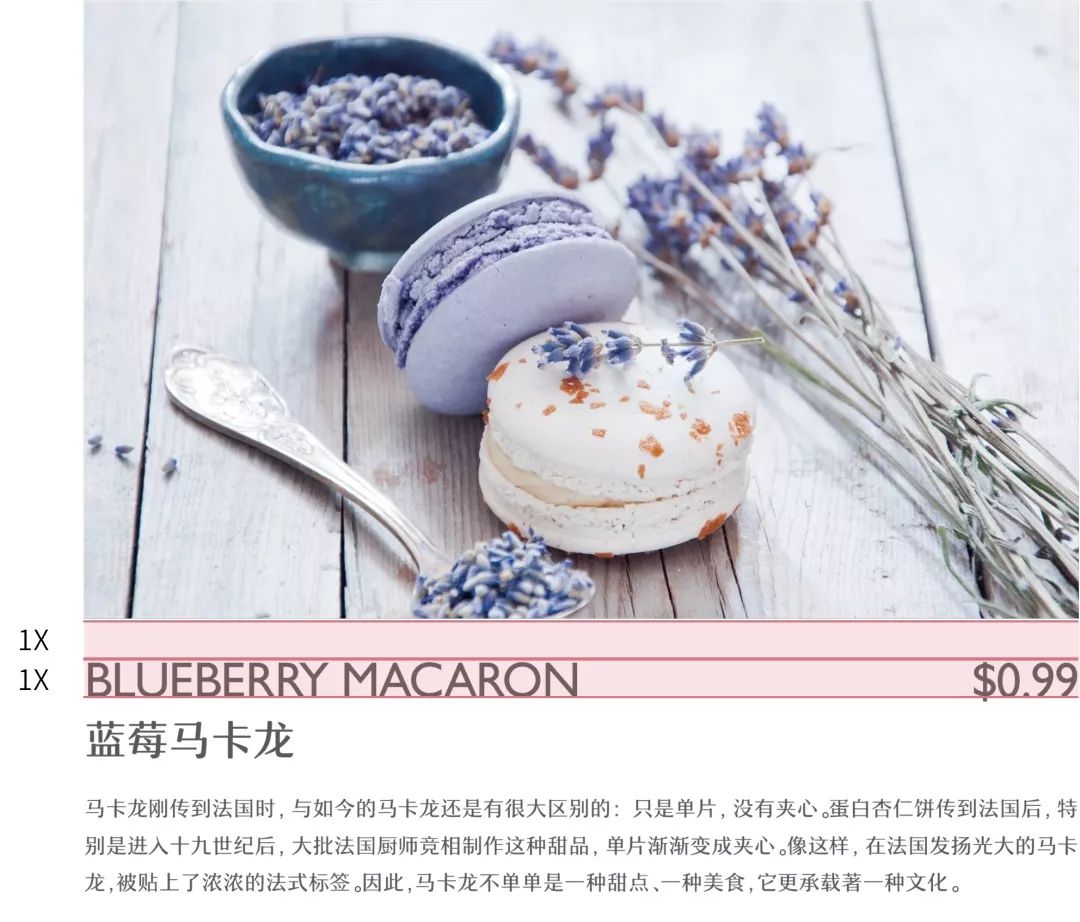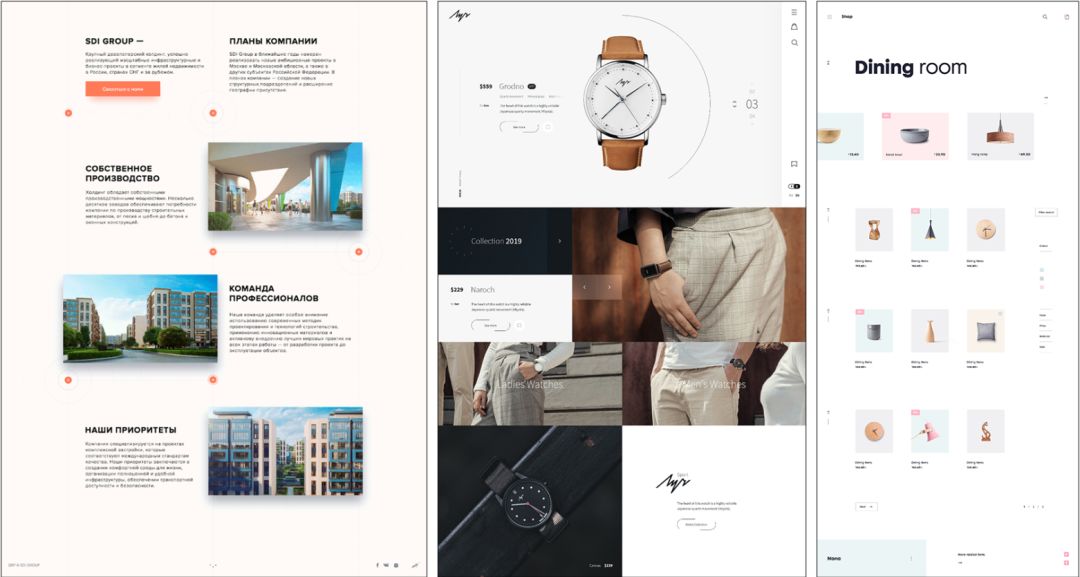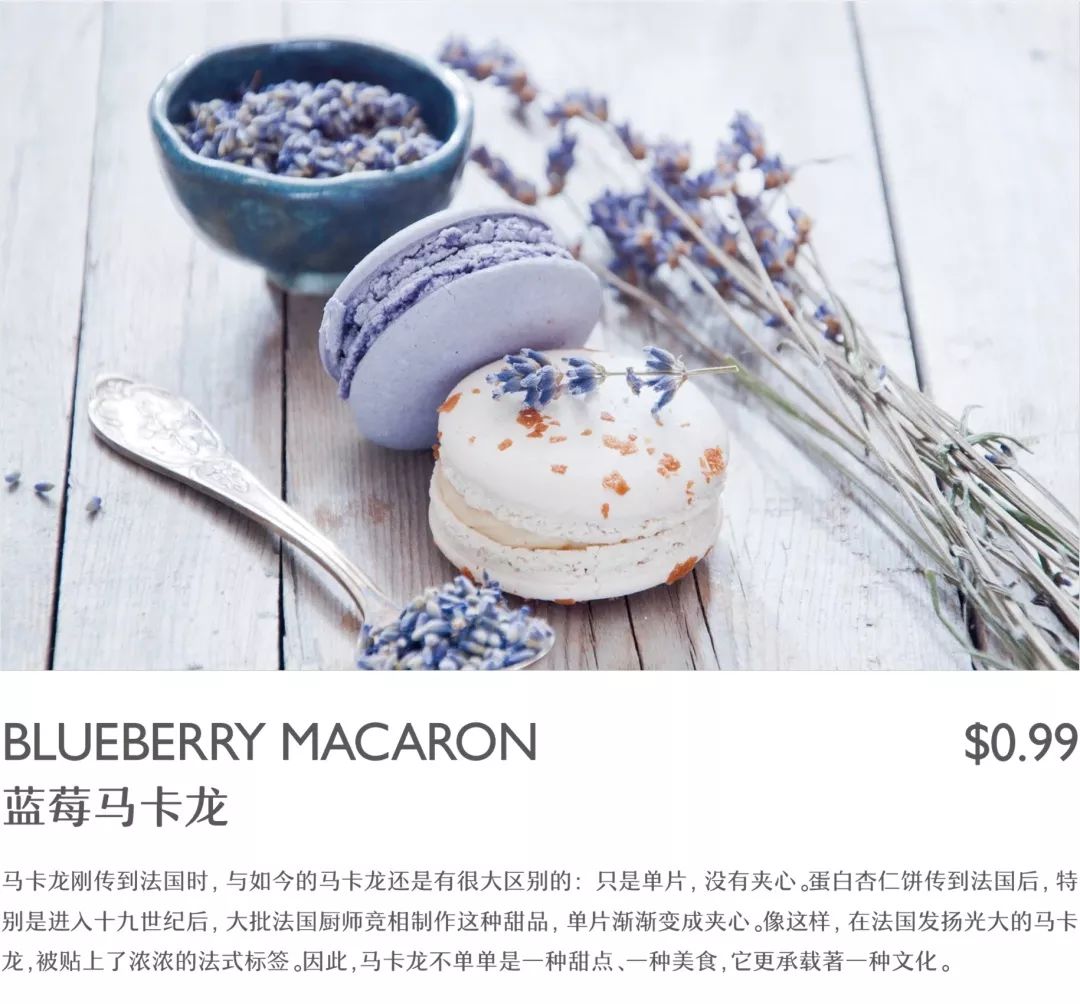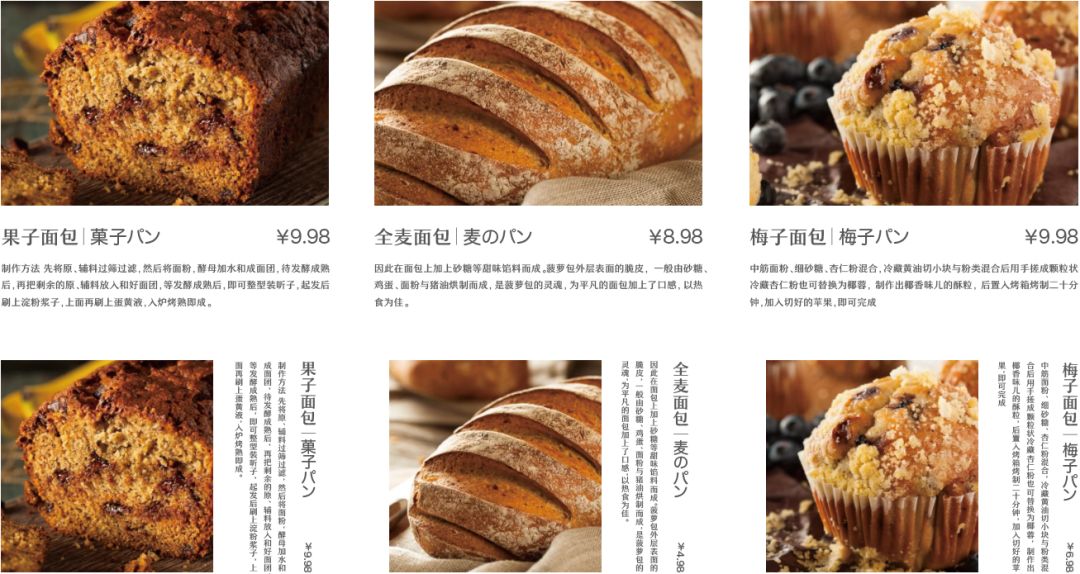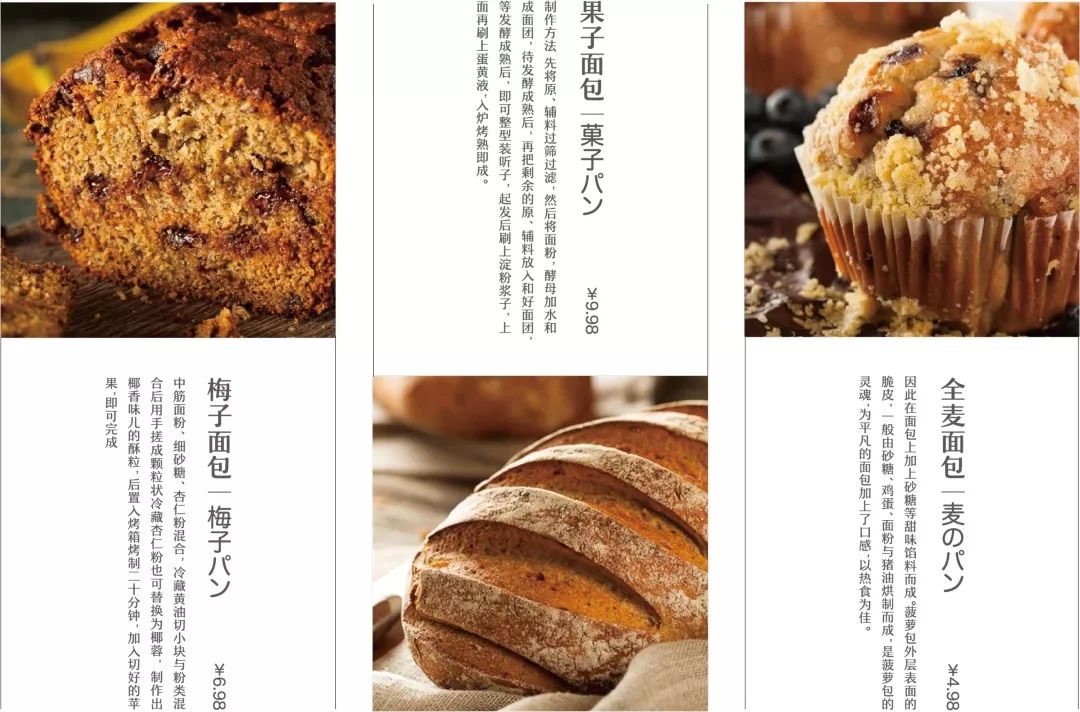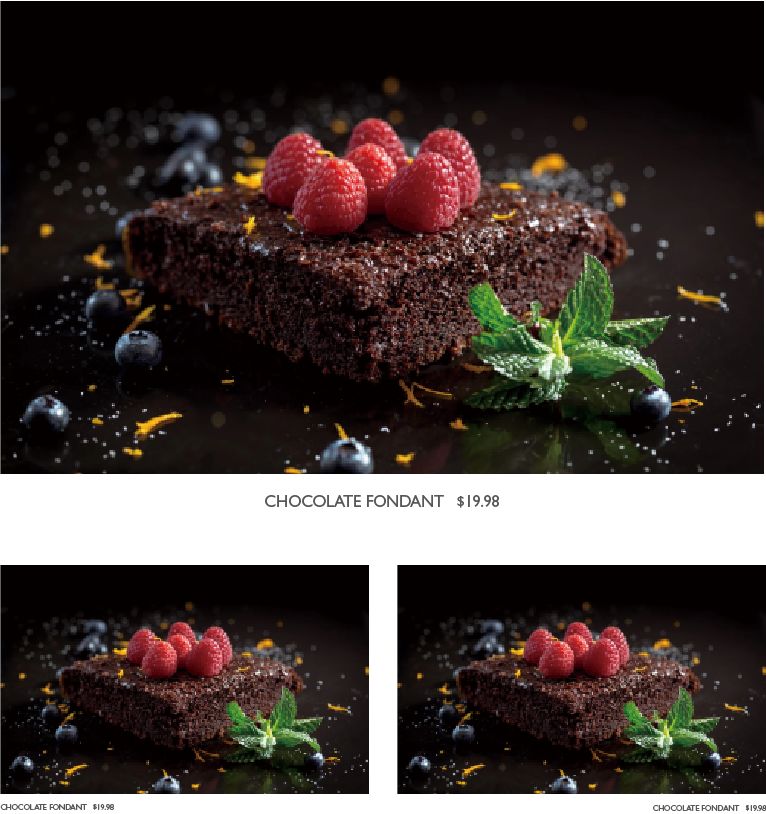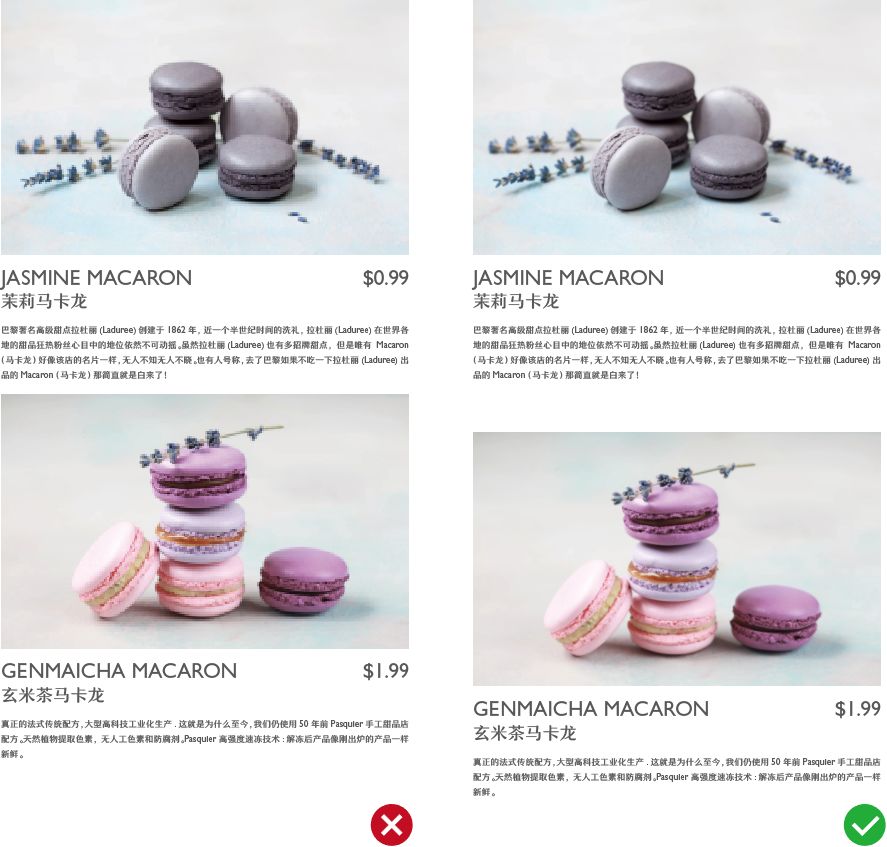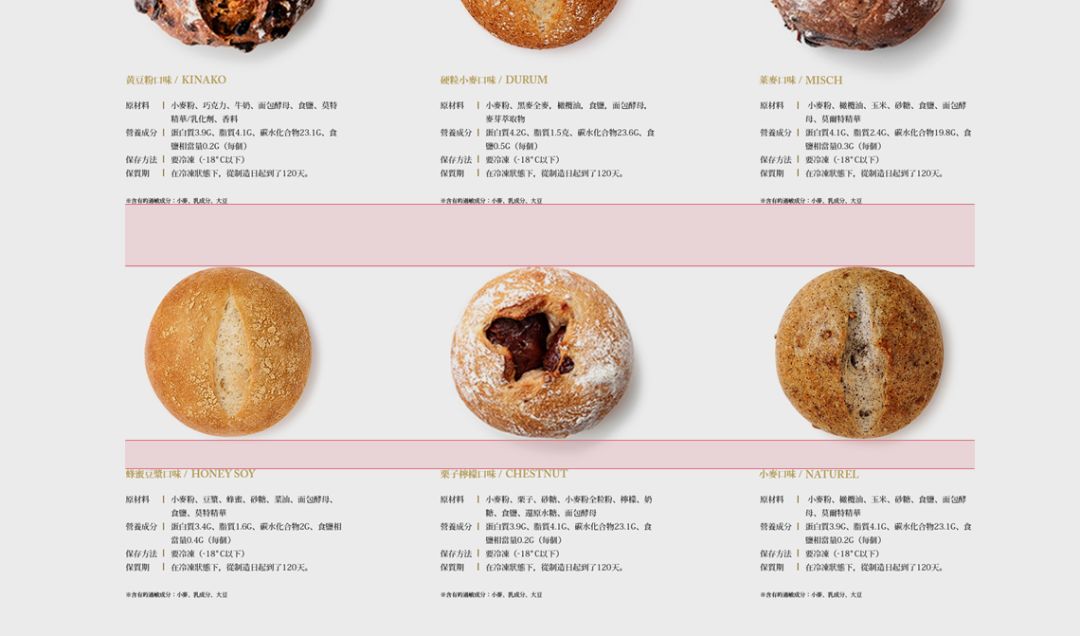
图文混排要注意哪些?图文混排的设计技巧
我们都知道,文字与图片是版面中重要的视觉元素,文字的排列决定了受众的阅读效果,而图片则更容易吸引受众的视线,而且在版面中,他们多数情况下都是一起出现的,所以说在我们的设计过程中,他们两者之间的编排形式就很重要了。那么这个看似简单的课题,又有哪些问题和细节是值得我们注意的?先来欣赏一些图文混排的作品。
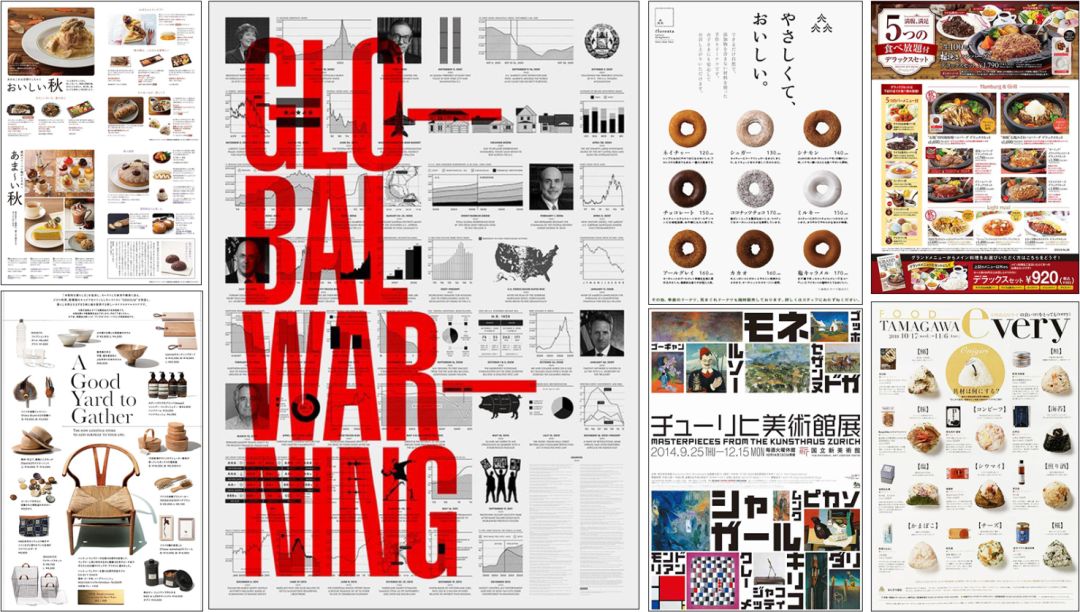
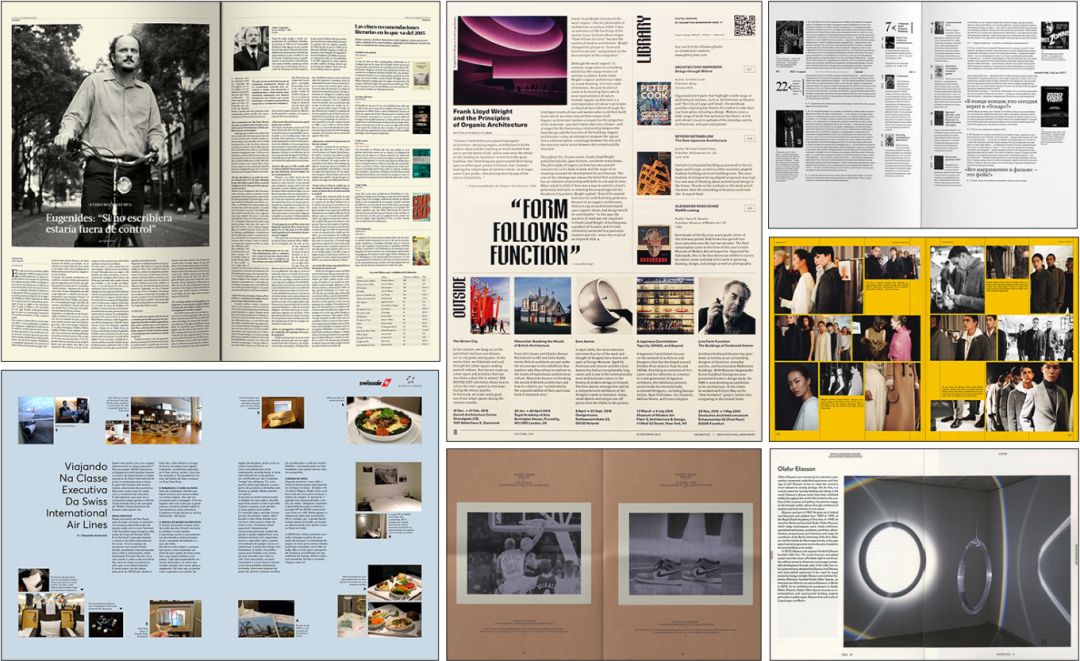
海报、DM、网页、长图、杂志、报纸等等媒介,都存在着大量图文混排的应用。
在我们进行图文混排的过程中,首先要注意的是图片与文字的距离。图片和文字放在一起的话,要么是文字说明图片,要么是图片表达文字的内容,也就是他们之间的内容是相关的,如果距离没有控制好,就会给读者带来阅读障碍。
来看一个小例子,如果版面中只有一张图片和一组文字,那么他们之间的距离只要不离的太近或太远,在保证美观度的情况下,都可以接受。
不过他们的距离特别近,就像现在这样,几乎贴在一起了或者特别远的情况,中间还没有其他的符号进行装饰,看起来就不是那么没美观了。
正常情况下,如果我们以文字作为参照物,一行文字的高度为1X,那么文字和图片的距离保持在一个文字的高度。
或者1.5X,包括两个字的高度都没问题,看起来还是比较舒服的,这是在一张图片和一段文字的情况下。
在版面中出现了两组或两组以上的图文组合,这个时候我们就不能单纯的考虑一组图文的距离了。
横排忽视距离的效果就会变成这样。
现在版面中的这两组图文,间隔距离如果太近,同样会造成版面混乱,信息传递不清晰,我们很难分辨出哪段文字是解释哪张图形的。当这两组图文的间隔距离加大,他们的关系就很明确了。版式设计的目的就是美观、清晰、快速的向外传递信息,尽量不要给读者的阅读设置这种障碍。
特别是在现在这个读屏的年代,可以去看看我们订阅号里的图文部分,因为内容都很长,所以每一组图文组合之间也都会留足够间隔距离,这就是为了方便大家阅读的设置,如果所有的内容都挤在一起,间距不明显就有点反人类了。
距离这块搞懂了,再来了解一下图片与文字的布局。在版式设计的过程中,图片与文字的布局也同样重要,我们不能单纯的为了美观,而忽视了文字的可读性。
比如版面中的这三组图文混排的信息,在正常情况下我们会根据版面的尺寸,设计成这两种常规的形式。不过这些形式,有的同学会觉得这样太普通了,想做点变化进去。
做了变化以后,再来看这种布局形式,同样很美观,很漂亮,但是文字与图片之间的联系就很模糊了,阅读的顺序让人摸不到什么规律,所以说这是一个形式上美观但功能性很弱的设计。
如果你就是想设计成这种形式的话,那么在图片与文字的组合之间,加入线来进行分割,才能缓解这个问题。
除了用线来做分割,解决这个问题的方式还有很多。比如同样是使用线条,我们还可以使用线的连接功能,将文字和其所对应的图片联系到一起,提醒受众,这段文字是用来解释这张图片的。
另外,我们还可以使用序号的标注,来强化提示文字与图片的联系。
包括利用的位置关系,将版面中图片、文字相对应,也可以很自然的把他们联系到一起,这些都是图文混排做变化,又不会影响阅读体验的小技巧。
再来看这个组合的形式,版式上看似没什么问题,但是这种把图片插在了段落文字中间的方式尽量不要使用。因为图片出现在这个位置会阻碍我们正常的视觉流动,读者在阅读这一整段信息的节奏会被打乱,产生不连贯的感觉,所以说这也是一个错误的案例。
换成竖排的文字,道理也一样,图片的布局要在不阻碍我们视线流动的基础上编排。
在图文混排的版面中,还需要注意这两种视觉元素的协调统一,统一的重要性在以前的内容里讲过了,它直接影响着整个版面的视觉效果。因此我们就应该想办法,尽量减少图片与文字之间不协调的感觉。
如果是文字量较多的段落文字,那么这种文字与图片宽度一致的方式属于统一性最强的。左右结构的话,最好也要保证他们的高度是一致的,这是秩序。
单纯的搞成这样,肯定是不舒服的。
要是文字量较少的标注、注解文字,我们保证文字信息与图片的对齐就可以。左对齐的、右对齐的、居中对齐的都很舒服。
如果文字的位置放在这种不左不右不居中的位置,想做统一就比较困难了。
在完整的图片内部加入文字信息的时候,文字信息一般都起到解释图片的作用,图片与文字做比较,图片相对更重要,是主体,这样的话我们做类似设计的时候就要注意文字不能抢了图片的风头、破坏图片的完整性。
文字与图片重叠,文字不要压住图片中的重点展示的位置,最吸引人的位置被压住了。结果就是现在这样,文字破坏了图片的美观度,阻碍了图形向外传递信息的速度。
如果文字是放在这几个地方,就完全没有问题,文字解释图片。
这张图片,当文字被安排在绿叶的位置,它的颜色再使用绿色就不太合适了,和图片这个区域的颜色太过接近,文字识别性变得很差。把文字换成白色,与图片进行区隔,就不会出现这个问题。
当然了,上面提到的是用文字来解释图形,如果我们用图形作为背景来说的话,他们的主次关系反转了,这就是另一回事了。
这是我们为这节课设计的案例,整个版式的形式,主要就是由图片与文字的混排构成的。里面在细节方面的控制,也都是遵循了我们前面的内容所提到的知识点,不管是整体的美感还是传递信息的方式都很舒服。
比如前面提到的图片与文字的距离问题,不远不近,正好合适。这里两组图文的间隔距离加大,也是为了不给读者的阅读增加负担。
当文字出现在图片内部的时候,注解类的文字不能压住图片中重点展示的位置。
包括前面讲过的其他注意事项,我们在欣赏优秀作品的时候都可以去有意识的观察,看看别人在做图文混排的时候是不是这样处理的。注意并理解了这些知识点以后,把他们应用到自己的设计过程中,这也是我们学习、提升的过程。
来总结一下今天的内容,在我们进行图文混排的时候要注意控制好图片与文字的距离,不要给读者设置障碍,图片与文字的布局不能为了美观而破坏文字的识别性,注意图片与文字的统一性,如果文字在图片中,文字不能破坏图片的完整性,颜色也需要有对比。